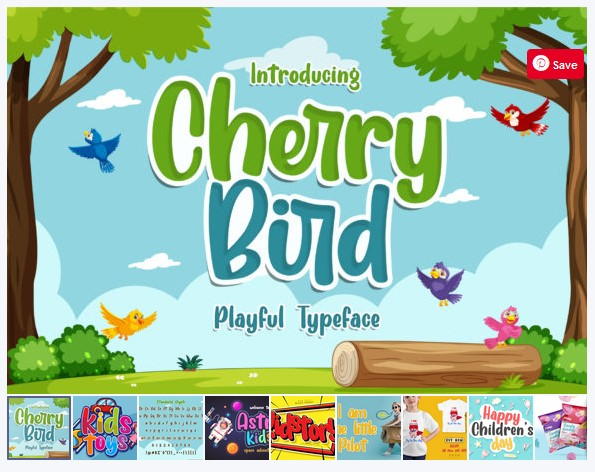
Cherry Bird Font
Cherry Bird это жирный и гладкий рукописный шрифт.
Он обладает игривым чувством, которое превратит любую крафтовую идею в настоящую выдающуюся.